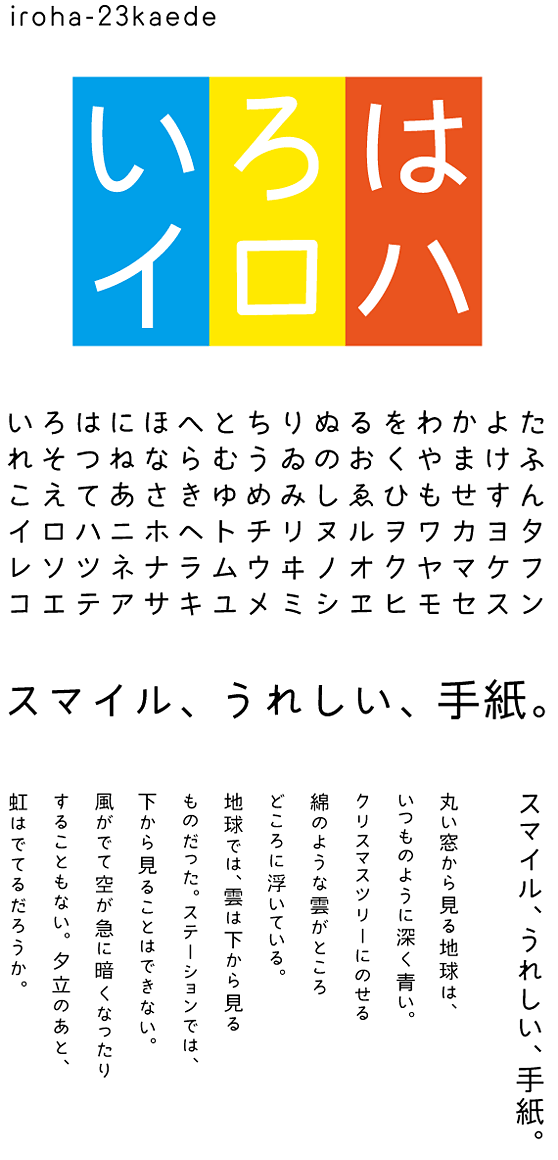
角ゴシック
iroha 23kaede (いろは23カエデ iroha 23kaede StdN R)
漢字は線の均一化を図り、モダンにしました。強さをだすために直線を意識し、安心感をだすためにふところを広くしています。先端部をあえて直角処理にしているため、漢字だけを組むとロゴタイプのような見え方をします。
irohaの名前どおり、かなの形の違いによって文字組の印象を変えることのできるシリーズになっています。
irohaシリーズ